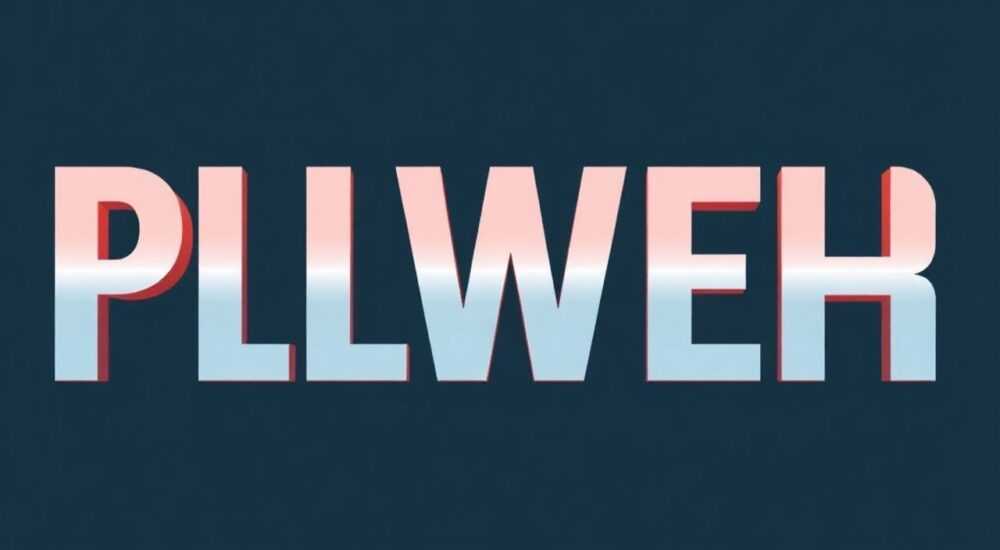
Как сделать шрифт толще в фотошопе
В графическом дизайне четкость и выразительность текста играет ключевую роль. Особенно остро этот вопрос встает, когда шрифт на изображении выглядит слишком тонким, теряется на фоне или не передает нужного акцента. Adobe Photoshop предоставляет множество инструментов для корректировки начертания текста, включая возможность сделать шрифт толще без потери качества. Это особенно важно при создании логотипов, заголовков, постеров и других материалов, где визуальное воздействие имеет первостепенное значение.
Чтобы сделать шрифт толще в Photoshop, используйте стиль слоя «Контур» (Stroke) или эффект «Насыщенность» (Bold через маскировку). Наиболее гибкий способ — применение обводки с небольшим размером и режимом наложения «Нормальный», что визуально утолщает буквы без потери четкости.
Как утолстить шрифт с помощью обводки (Stroke)
Один из самых популярных и простых способов — добавление обводки к текстовому слою. Этот метод работает за счет наложения тонкой линии по контуру каждой буквы, что визуально делает их толще. Чтобы применить обводку, выберите текстовый слой в панели «Слои», щелкните правой кнопкой мыши и выберите «Стили слоя» → «Обводка». В открывшемся окне установите размер обводки от 1 до 3 пикселей — этого обычно достаточно для естественного эффекта.
Важно правильно выбрать положение обводки: «Внутри», «По центру» или «Снаружи». При выборе «Внутри» обводка будет накладываться внутрь контура буквы, что может немного сгладить мелкие детали. «Снаружи» — идеален, если нужно сохранить исходную форму символа. «По центру» делит обводку пополам, что иногда приводит к размытости. Для четкого результата рекомендуется использовать режим наложения «Нормальный» и цвет, совпадающий с текстом.
Шаги применения обводки:
1. Выделите текстовый слой в панели «Слои».
2. Перейдите в меню «Слой» → «Стиль слоя» → «Обводка».
3. Установите размер (1–3 px), положение («Снаружи») и цвет (совпадающий с текстом).
4. Нажмите «ОК» и оцените результат.
Полезно знать: Если после обводки текст стал выглядеть размыто, проверьте разрешение холста. Обводка на низком DPI может потерять четкость. Работайте с документами от 150 ppi и выше.
Использование стилей наложения и эффектов
Photoshop позволяет утолщать шрифт не только через обводку, но и с помощью комбинированных эффектов. Например, можно использовать «Тень» с нулевым размытием и смещением X/Y = 0, чтобы создать эффект объемного заполнения. Другой подход — дублирование текстового слоя и небольшое смещение копии вниз и влево, затем объединение через «Объединить снизу» (Ctrl+E).
Более продвинутый способ — применение фильтра «Размытие по Гауссу» к дубликату текста с последующей настройкой прозрачности. Это создает мягкий эффект утолщения, который хорошо подходит для художественных проектов. Однако такой метод требует аккуратности: чрезмерное размытие сделает текст нечитаемым.
Метод
Преимущества
Недостатки
Обводка (Stroke)
Четкий результат, легко контролировать
Может искажать мелкие детали при большом размере
Дублирование слоя
Полный контроль над формой
Требует ручной корректировки, не масштабируется
Фильтр размытия
Мягкий, художественный эффект
Риск потери четкости
Альтернатива: использование плагинов
Для профессионалов доступны сторонние плагины, такие как «Typetool» или «Fontself», которые позволяют редактировать контуры шрифтов напрямую. Они дают больше свободы, чем встроенные инструменты, и могут автоматически утолщать символы с сохранением пропорций. Однако такие решения требуют дополнительной установки и обучения.
«Использование обводки — это быстрое решение, но для брендовых проектов лучше перейти к векторному редактированию. Искусственное утолщение может нарушить баланс начертания.» — Алексей Миронов, арт-директор, 12 лет в типографском дизайне
Работа с векторными контурами и расширением букв
Если вам нужно максимально точное и качественное утолщение, переходите к редактированию контуров текста. Сначала преобразуйте текстовый слой в фигуру: кликните правой кнопкой по слою → «Создать контуры». Теперь текст становится векторным объектом, и вы можете редактировать его точки с помощью инструмента «Перо» или «Прямое выделение».
Для равномерного утолщения используйте команду «Выполнить обводку контура» (в меню «Контур»). Выберите инструмент «Кисть» с жесткими краями и диаметром, соответствующим желаемой толщине. Затем активируйте контур (Ctrl+Enter) и примените обводку. Полученный слой можно залить сплошным цветом, и результат будет выглядеть как действительно жирный шрифт.
Процесс по шагам:
1. Преобразуйте текст в контуры (ПКМ по слою → «Создать контуры»).
2. Откройте панель «Контур» и активируйте контур текста.
3. Выберите инструмент «Кисть» с нужным диаметром.
4. Нажмите «Выполнить обводку контура».
5. Создайте новый слой под текстом и выполните обводку на нем.
6. Залейте результат и скройте исходный текст при необходимости.